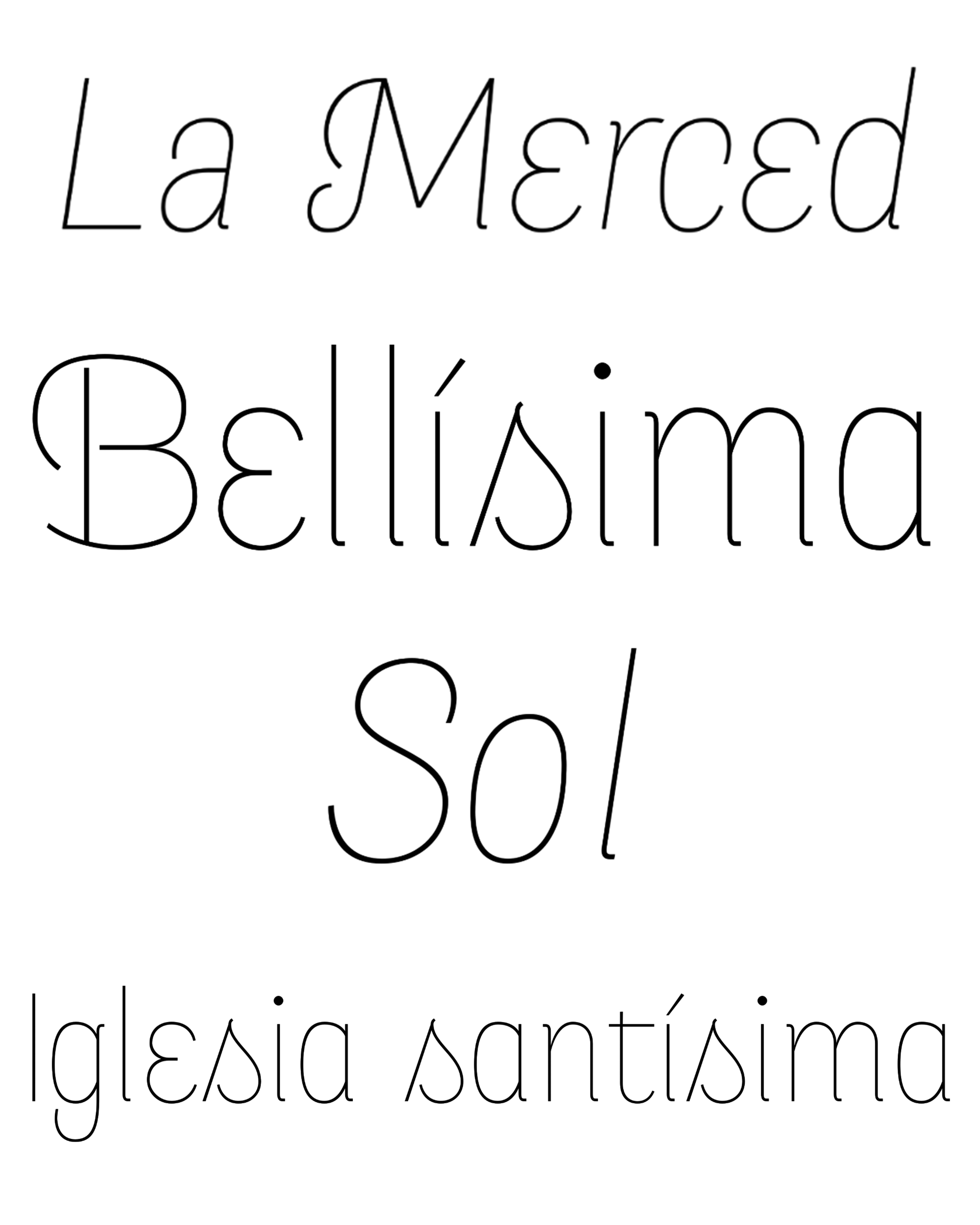
| Descripción | Una sans serif fresca, rizada y deliciosa. Diseñada por Daniel Hernández, Merced es una fuente sans serif que ofrece diversos usos gracias a su amplia variedad de tipos alternativos. Su principal virtud reside en sus infinitas posibilidades para escribir palabras, textos o párrafos. Idiomas: latín básico, europeo occidental, europeo, catalán, báltico, turco, centroeuropeo, rumano y latín panafricano. |
| Familia(s) | Luz de la Merced, Merced Light Italic |